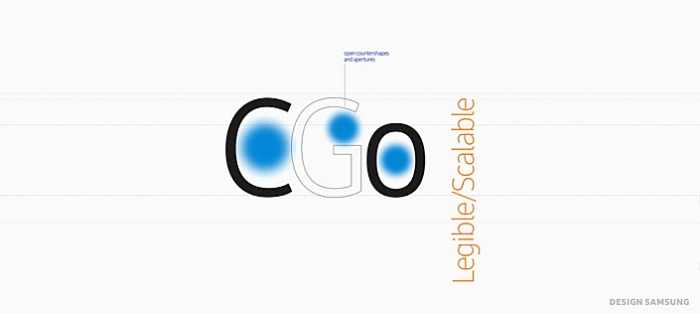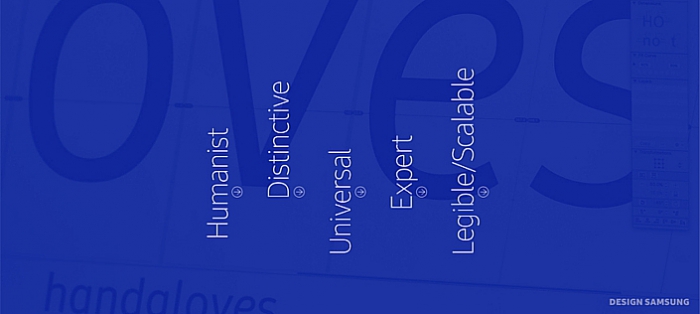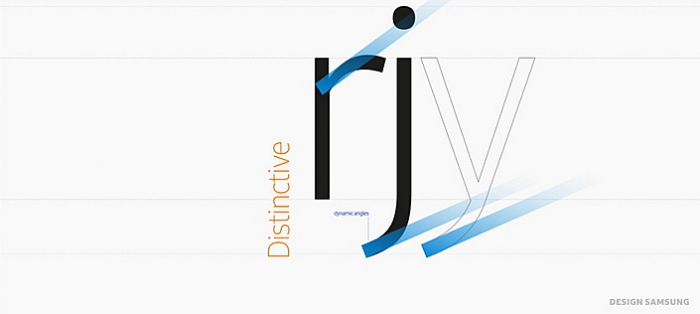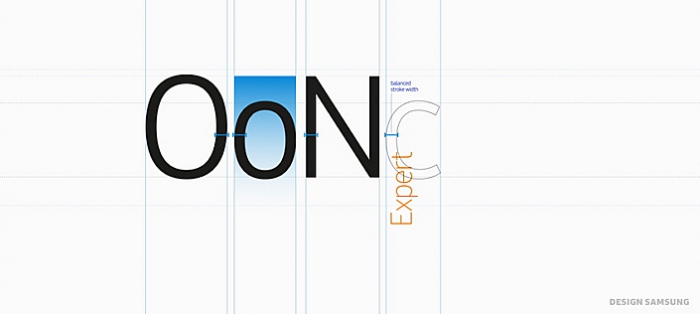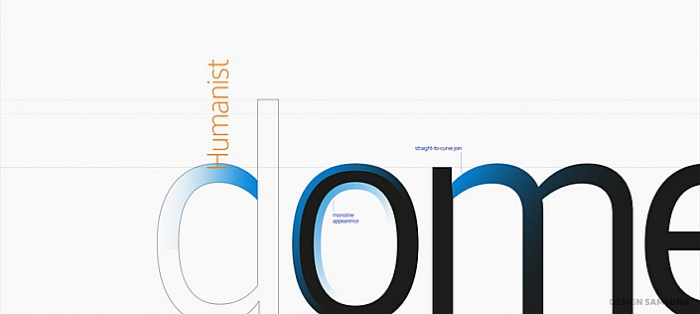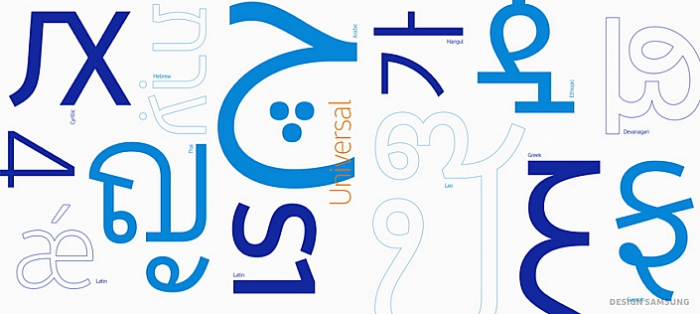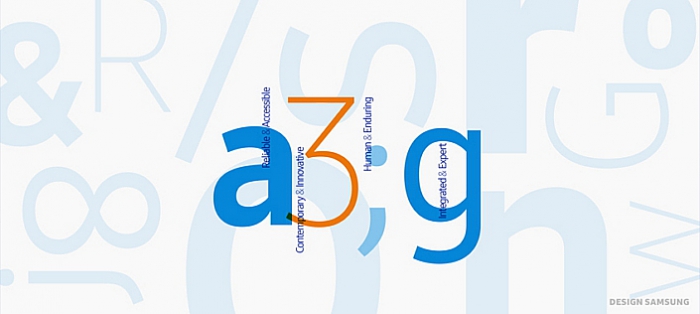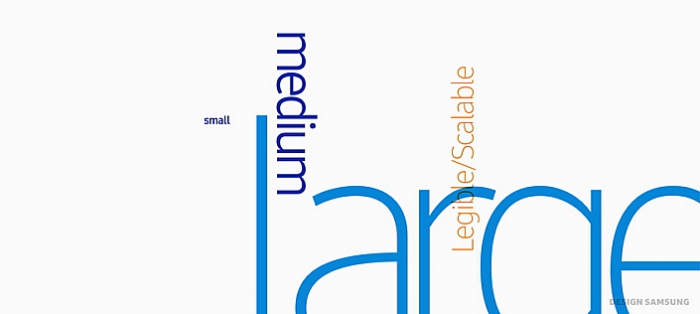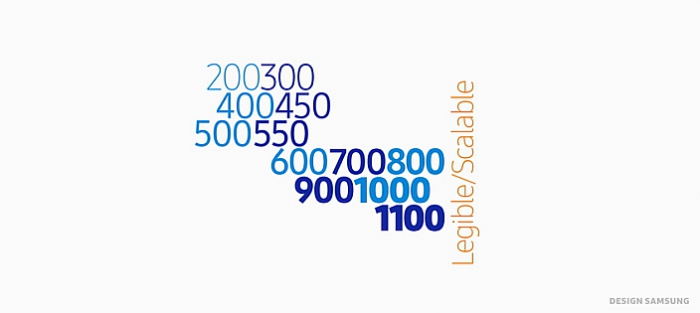
Деятельность Samsung Electronics связана с различными продуктами, платформами, людьми и культурами. Компания решила передать универсальность опыта с помощью собственного шрифта. SamsungOne представляет собой семейство шрифтов, которое включает 26 систем письма, более 400 языков и свыше 25 тысяч символов.
Пользователи открывают Samsung через продукцию, бренд-платформу и связанную с брендом культуру. SamsungOne должен стать центральной частью открытия, составным элементом пользовательского опыта. Потребители будут видеть шрифты, принимая телефонный звонок, глядя любимое шоу на ТВ, включая бытовую технику, разглядывая упаковку или рекламные материалы. Samsung Electronics выпускает мобильные телефоны и телевизоры, ноутбуки и микроволновки, духовые шкафы и планшеты. SamsungOne позволит объединить все эти устройства.
Как заявляют в компании, фирменный шрифт находится в самом сердце ДНК нового визуального языка. SamsungOne — солидный, жизнеутверждающий и четкий, выполнен в теплых тонах. Он прекрасно смотрится и в большом, и в малом масштабе. Над созданием шрифта трудился известный типограф Нэвилл Броди.